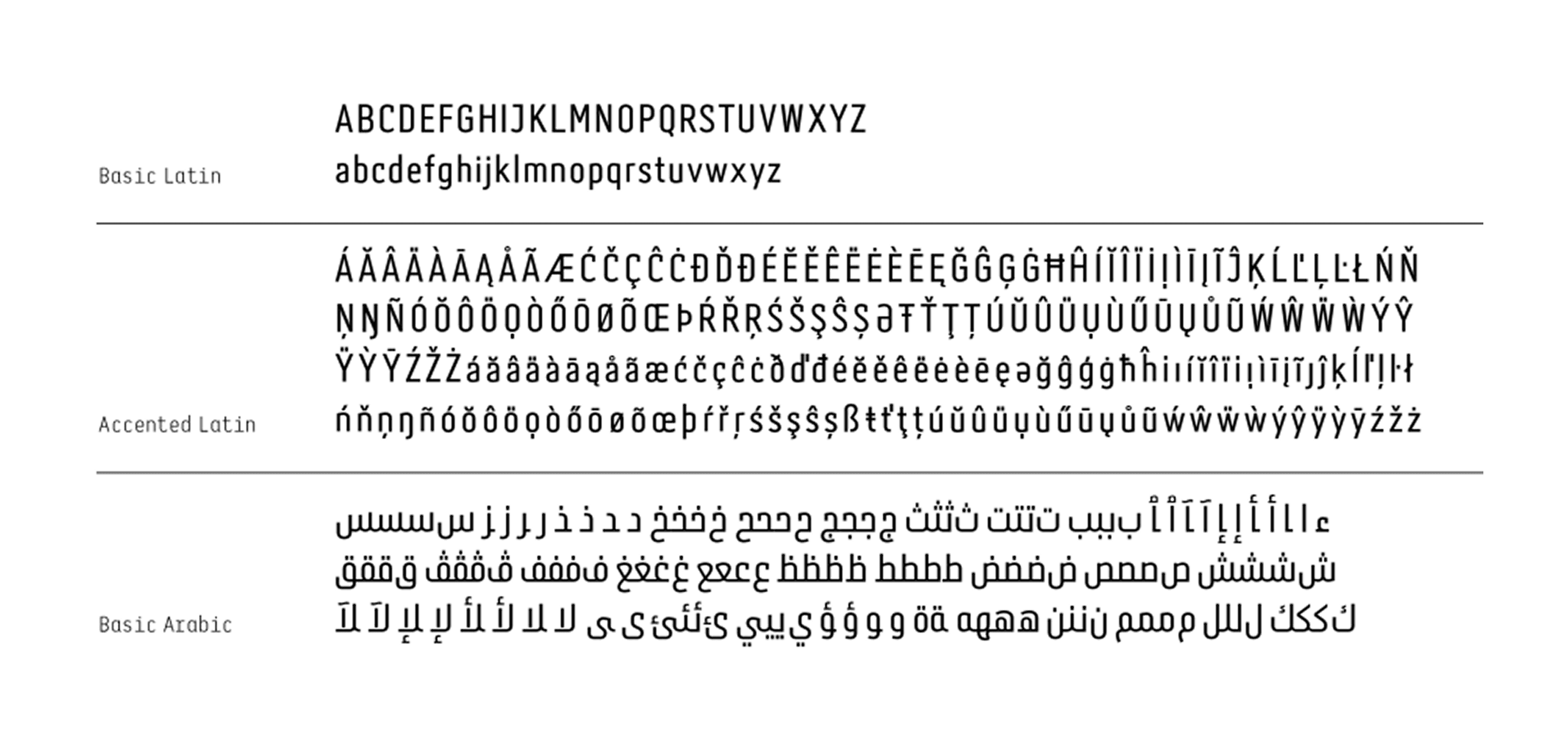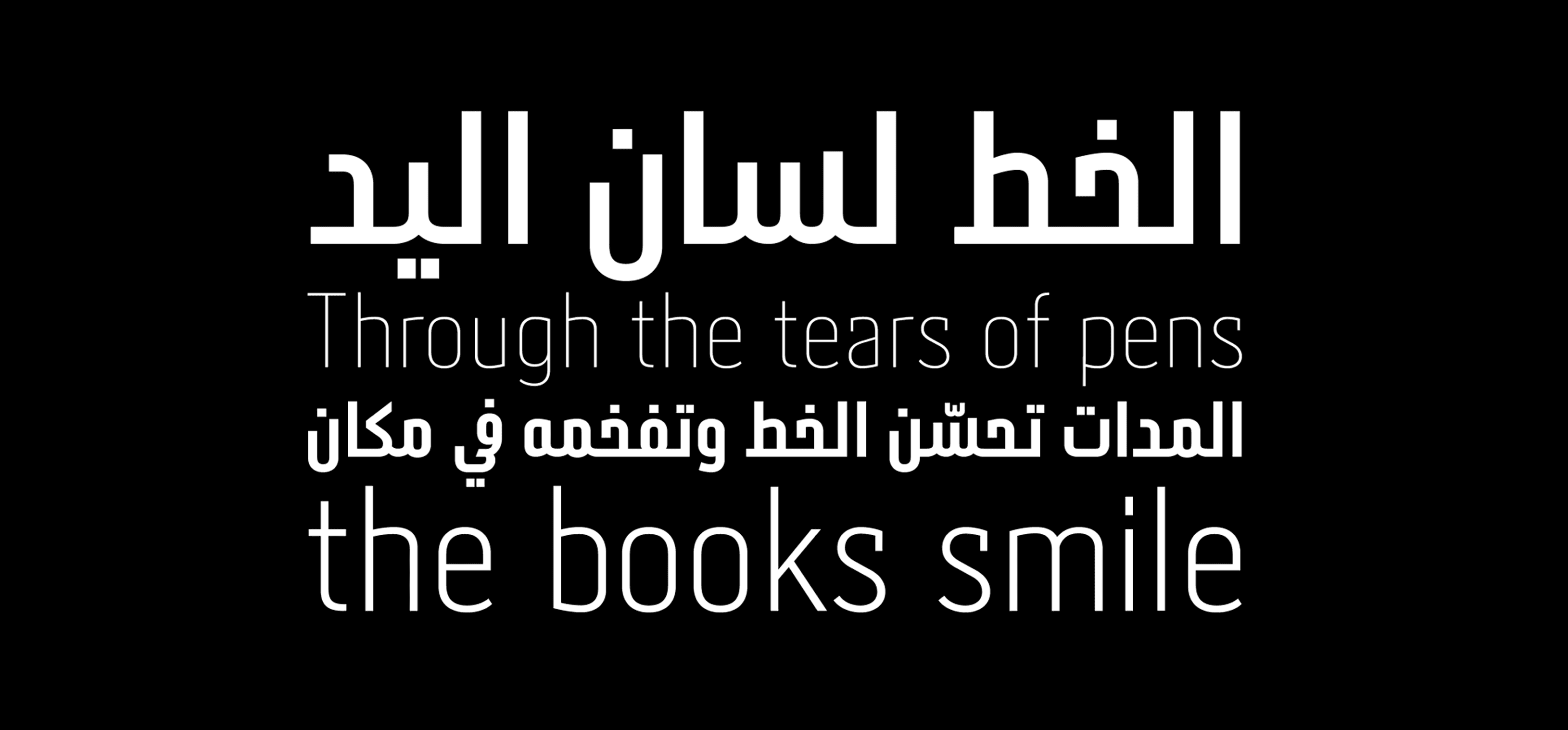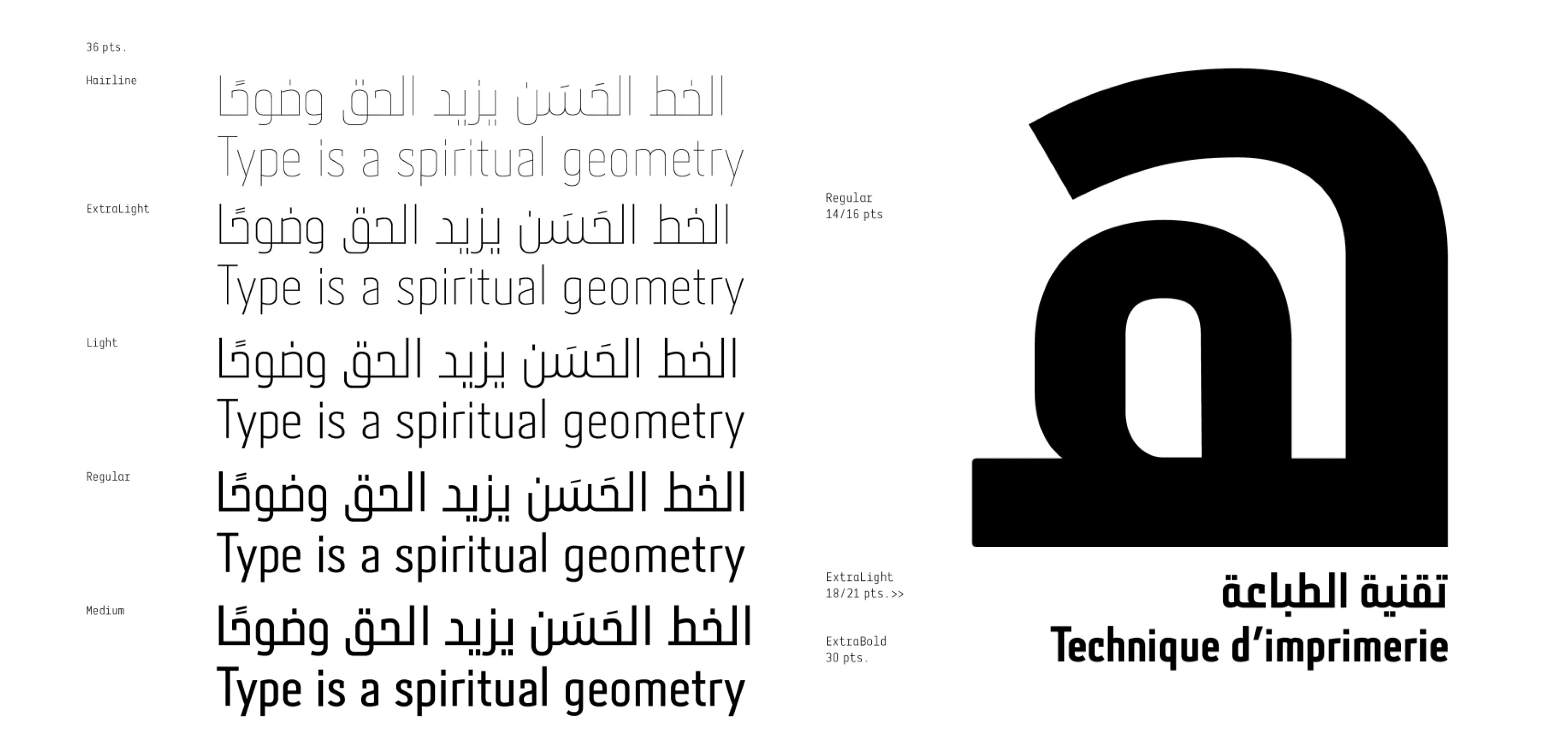
يمثل خط "قدير" مزيجًا مثاليًا بين الخط العربي الهندسي (نسخ حديث) والخط اللاتيني الخالي من الزوائد (Sans Serif)، صُمم بعناية ليُظهر الكفاءة والاحتراف. يتميز بتصميمه العصري النظيف وتوفّره في أكثر من 8 أنماط مختلفة، مما يجعله مناسبًا للاستخدام في العناوين، الشعارات، والتصميمات الطباعية التي تتطلب وضوحًا وقوة حضور.